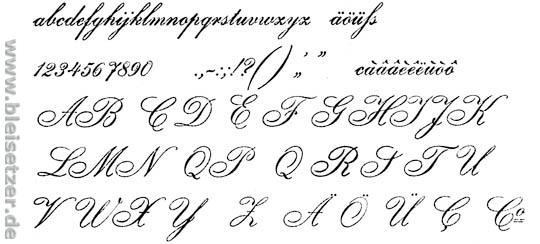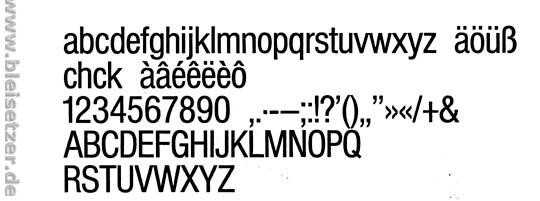
Ungeschriebenes Gesetz für Schriften Mix?
Mich beschäftigt schon seit einiger Zeit die Frage, ob es in der Schriftorientierten Praxis eine Art ungeschriebenes Gesetz gibt, welches bestimmt, dass bestimmte Schriften (oder Schriften generell) nicht zusammen gemischt werden dürfen.
Ich persönlich finde es sehr unschön wenn man mehr als 3 versch. Schriften in einem Text resp. Layout verwendet. Nun gut, ehrlich gesagt schon bei 2 verschiedenen. Höchstens einen anderen Schriftschnitt z.B. Bold Titel und mit Light den Text verfasst.
Im Moment machen wir in der Schule gerade eine Übung für unser nächstes Semester in dem wir "Kreative Techniken" als Hauptfach haben. Die Aufgabe ist es eine Schmalgrotesk mit einer Anglais zu kombinieren. Einfach so als Gestaltung finde ich es schon speziell aber in einem Layout, z.B. für ein Magazin wär mich das zu unschön.
Würde man Schriften nicht mischen sollen, gäbe es keine Auszeichnungsschriften. Denn dann wäre man ja gezwungen, Auszeichnungen innerhalb derselben Schriftenfamilie zu realisieren. Jede Schrift wäre dann gleichzeitig auch - in anderem Schriftgrad oder Version - Auszeichnungsschrift.
Eine Englische Schreibschrift mit einer schmallaufenden Grotesk zu mischen, wäre nicht unbedingt das, was mir als Ideal einfiele, aber warum nicht?
Um es einmal optisch darzustellen:
Lithographia
Helvetica schmalmager
Es hängt doch nur z.B. von der gewählten Schriftgröße ab oder auch von der Nutzung von Freiräumen, um beiden Schriften Wirkung zu geben.
Also ich halte mich da gerne an meine oberste Typo-Regel: Schauen.
Zwei mögliche Parameter für den Schriften-Mix: Harmonie und Kontrast
Zwei Schriften die sehr stark miteinander Harmonieren, kann man ungestüm auch in der selben Schriftgröße, also ohne Kontrast, problemlos mischen — und dabei wenig falsch machen.
Bei anderen Kombinationen wird es schwieriger. Die königliche Bodoni harmoniert beispielsweise überhaupt nicht mit dem ruppigen Handwerker Gill. Und dann noch eine Moby dazu. Da muss schon ordentlich Kontrast und handwerkliches Können rein um diese Suppe nicht zu versalzen.
Vielen Dank für die Antworten! Ja, die Beispiele leuchten ein @ Designworker. Leider sieht man immer wieder solche unpassende Mischungen wie z.B. eine Bodoni mit einer Moby!
Unser Lehrer hat gesagt, dass sich die Schriften z.B. bei Titel und Text möglichst stark unterscheiden sollten. Die Schriften können sich z.B. durch Schriftcharakter, Schriftschnitt und Grösse unterscheiden.
Ich denke zu einer Bodoni würde eine Times nicht schlecht wirken :D